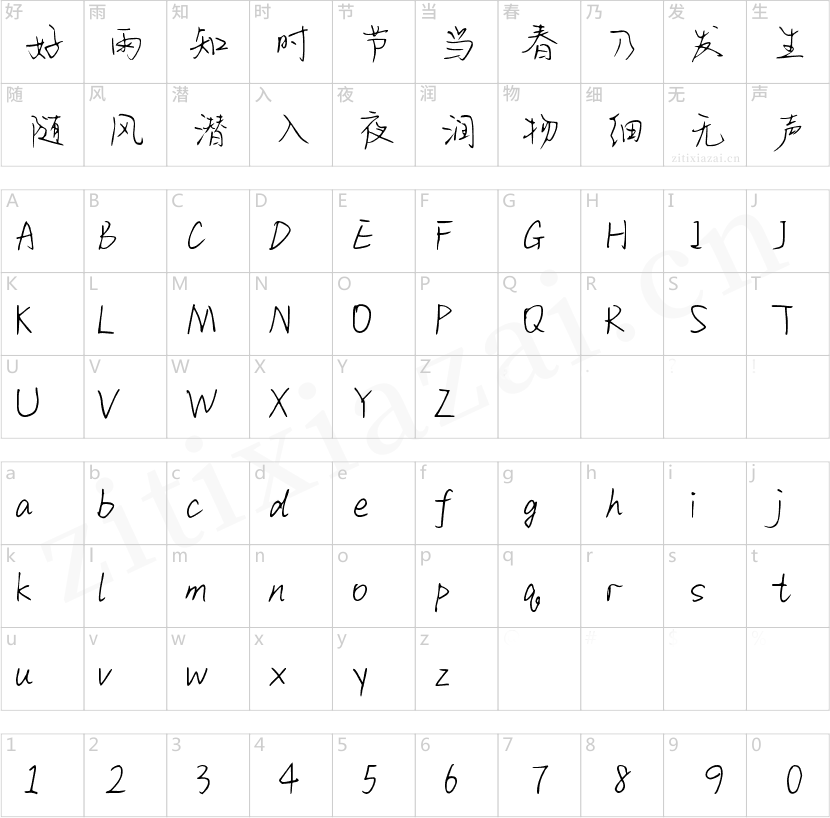
Aa相思寄山海
Aa相思寄山海字体
Aa相思寄山海是一款非常具有艺术性的字体,它的设计灵感来源于对古典艺术的研究,同时又融入了现代字体设计的元素。字形优美,笔画粗细变化自然,给人以大气、典雅的感觉。Aa相思寄山海是一款既传统又现代的字体,它的设计充满艺术感,美观大方,实用性也非常强。无论是对于设计师还是对于普通读者来说,都是一种非常不错的字体选择。Aa相思寄山海适合用于具有艺术感的场合,比如海报、宣传单张、书籍封面等。由于其字形流畅且具有动态感,也适合用于大量的文本排版,如报纸、杂志等。
Aa相思寄山海详情